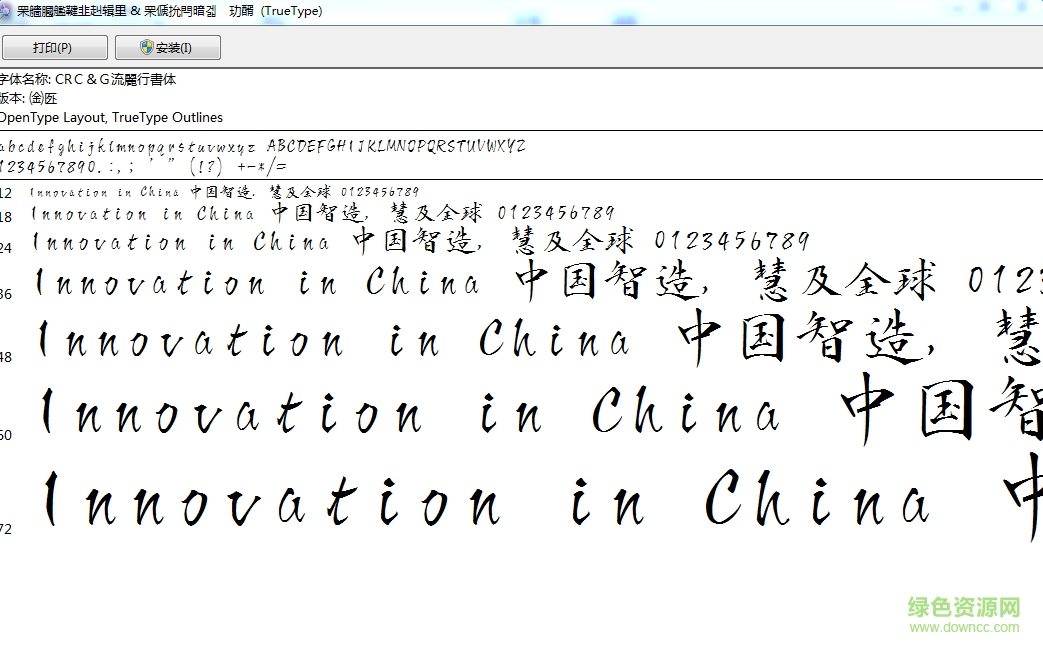
c g流麗行書(shū)體繁/簡(jiǎn)
c g流麗行書(shū)體繁/簡(jiǎn)字體是一款好看的行書(shū)字體,流暢瀟灑,具有不錯(cuò)的設(shè)計(jì)感,絕對(duì)雅俗共賞,可以用在藝術(shù)設(shè)計(jì)、古風(fēng)海報(bào)等方面,歡迎需要的朋友來(lái)綠色資源網(wǎng)下載!